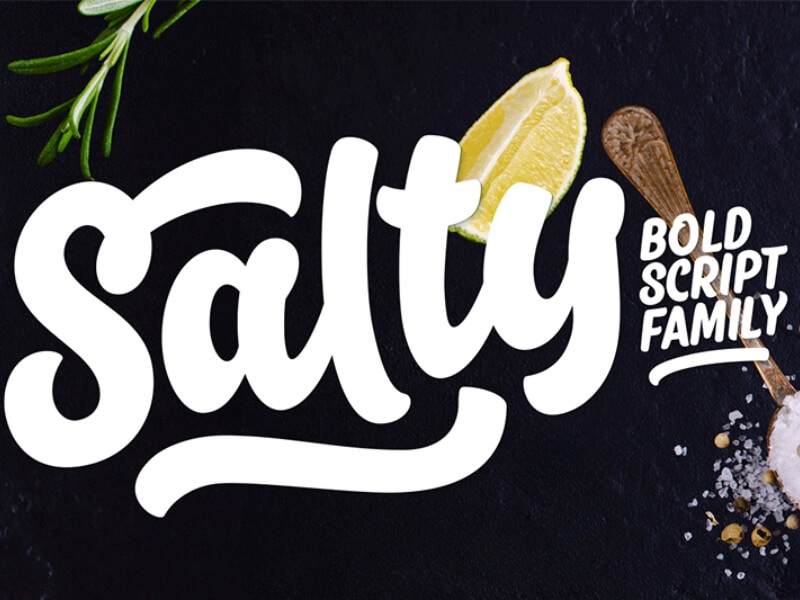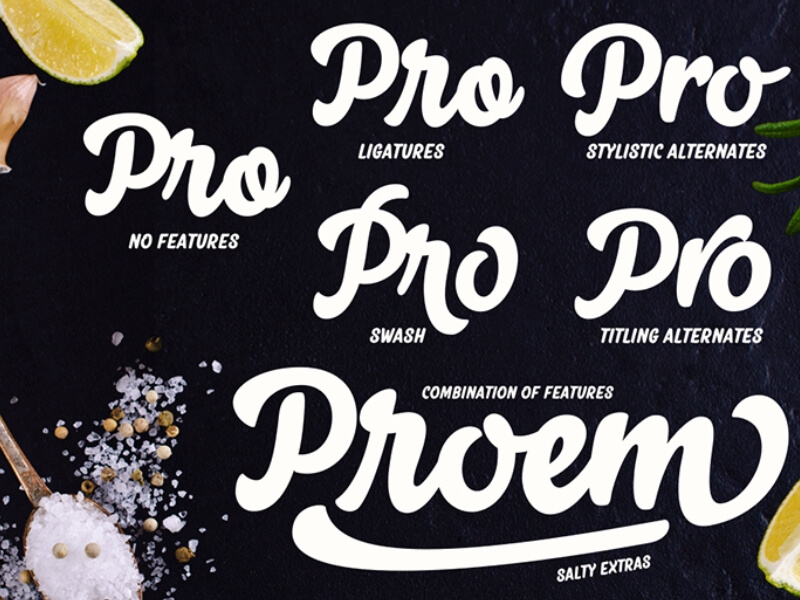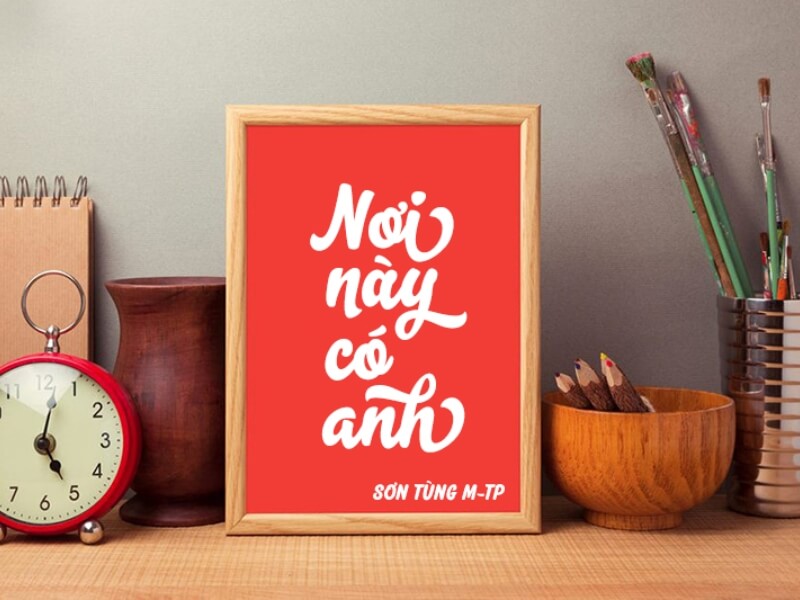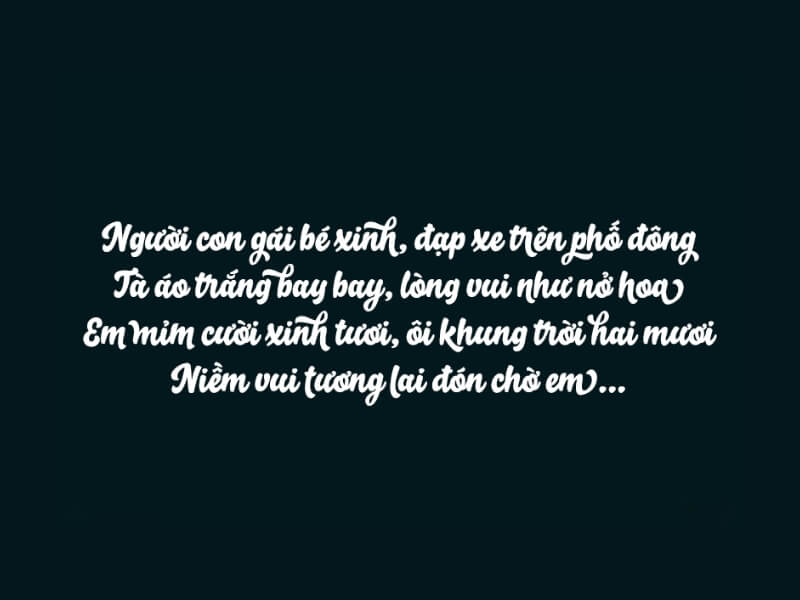
Font Việt hóa SVN Salty Script là kiểu chữ viết tay mang phong cách phóng khoáng, đậm chất brush, giúp tạo điểm nhấn mạnh mẽ và cá tính trong các thiết kế. Tuy nhiên, không phải phiên bản nào trên mạng cũng đảm bảo hiển thị chuẩn tiếng Việt, nhiều font vẫn gặp tình trạng lỗi dấu hoặc thiếu ký tự khi sử dụng.
Font SVN Salty Script việt hóa nổi bật với nét chữ viết tay bay bổng, phù hợp cho các thiết kế logo, poster, bao bì và ấn phẩm sáng tạo. Phiên bản việt hóa hỗ trợ đầy đủ dấu tiếng Việt, giúp bạn sử dụng dễ dàng mà không lo lỗi font. Dưới đây là 5 phiên bản font SVN Salty Script Việt hóa:
Phiên bản font |
Đặc điểm |
Ứng dụng |
SVN Salty Script Regular |
Nét chữ viết tay mềm mại, bay bổng | Logo, tiêu đề, poster, bao bì |
| SVN Salty Script Bold | Nét đậm, nổi bật hơn |
Banner quảng cáo, tiêu đề lớn |
| SVN Salty Caps | Chữ in hoa, nét cọ mạnh mẽ |
Tiêu đề, slogan, thiết kế cá tính |
| SVN Salty Extras | Ký tự trang trí, swash nghệ thuật |
Trang trí chữ, thiết kế sáng tạo |
| SVN Salty Alternates | Nhiều biến thể ký tự |
Thiết kế logo độc đáo, typography |
Đặc điểm nổi bật của font SVN Salty Script Việt hóa
Font SVN Salty Script gây ấn tượng với phong cách script brush đậm nét, mũm mĩm, mang lại cảm giác viết tay tự nhiên nhưng vẫn mạnh mẽ và nổi bật. Đây là lựa chọn lý tưởng cho các thiết kế cần sự cá tính và thu hút. Dưới đây là những đặc điểm nổi bật của font:
- Phong cách brush lettering độc đáo: Nét chữ đậm, chắc và có độ “nảy”, tạo cảm giác thân thiện nhưng vẫn mạnh mẽ, rất phù hợp cho tiêu đề và thiết kế cần điểm nhấn.
- Tính linh hoạt cao với OpenType: Font tích hợp nhiều tính năng như ligatures (nét nối), swash (nét lượn) và alternates (ký tự thay thế), giúp bạn dễ dàng tùy biến kiểu chữ theo nhiều phong cách khác nhau.
- Việt hóa hoàn chỉnh: Hỗ trợ đầy đủ ký tự tiếng Việt, dấu thanh được thiết kế hài hòa với tổng thể font, đảm bảo hiển thị đẹp khi thiết kế và in ấn.
- Tính thẩm mỹ nổi bật: Kiểu chữ dày, tròn và giàu năng lượng, tạo cảm giác trẻ trung, sáng tạo và thu hút ánh nhìn.
- Dễ kết hợp trong thiết kế: Bộ font thường đi kèm cả Script (nét liền) và Caps (chữ in hoa), giúp bạn linh hoạt phối hợp để tạo bố cục hài hòa và chuyên nghiệp.
- Ứng dụng đa dạng: Phù hợp cho logo, bao bì sản phẩm, poster, banner và các ấn phẩm truyền thông cần phong cách sáng tạo, năng động.
Ứng dụng của font Việt hoá SVN Salty Script
Font SVN Salty Script Việt hóa được ứng dụng rộng rãi trong nhiều lĩnh vực thiết kế nhờ phong cách viết tay đậm nét, cá tính và giàu tính nghệ thuật. Với khả năng tạo điểm nhấn mạnh mẽ, font đặc biệt phù hợp cho các ấn phẩm cần sự nổi bật và thu hút.
- Thiết kế logo thương hiệu cá nhân, shop thời trang
- Poster, banner quảng cáo sáng tạo
- Bao bì sản phẩm, hộp quà tặng
- Thiệp mời, thiệp cưới, card chúc mừng
- Nội dung mạng xã hội (Instagram, Facebook, TikTok)
- Dùng đúng mục đích: Đây là font viết tay, phù hợp cho tiêu đề, logo, slogan. Không nên dùng cho đoạn văn dài vì sẽ khó đọc.
- Tận dụng tính năng font: Có thể dùng thêm ligatures, swash hoặc ký tự thay thế trong bảng Glyph để chữ đẹp và đa dạng hơn.